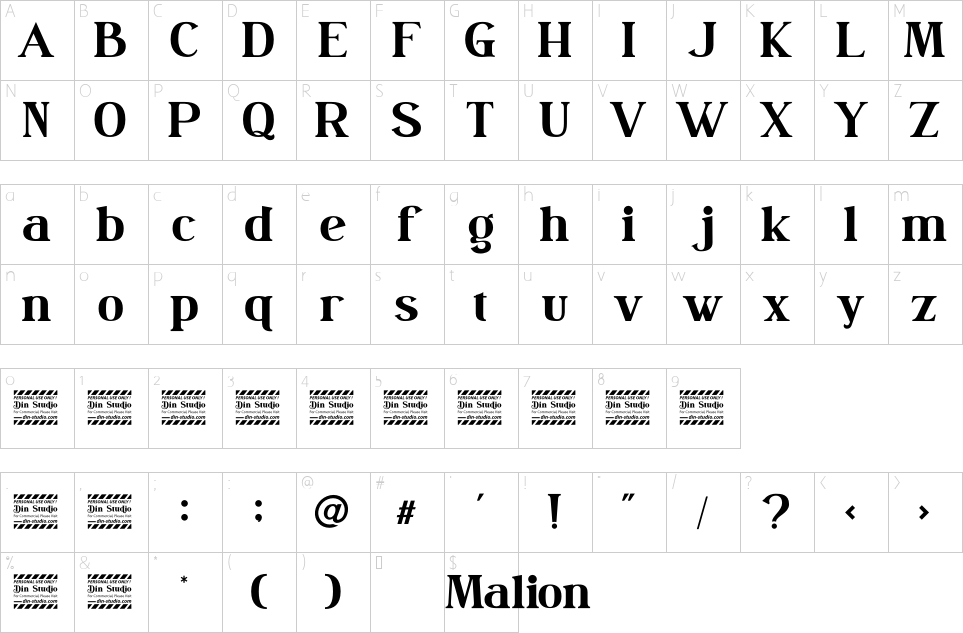
A Malion Font é uma fonte de graça ideal para designers e criadores de conteúdo que buscam uma opção moderna e elegante. Desenvolvida pela Din Studio, esta fonte oferece uma variedade de tamanhos e estilos, tornando-a perfeita para diversas aplicações de design, desde logotipos e gráficos até designs web e publicações digitais. Com seu design minimalista e arquitetado para um uso fluido, a Malion Font é uma escolha ideal para quem busca uma fonte clara e moderna para seus projetos. A fonte foi baixada cerca de 3,584 vezes, demonstrando sua popularidade entre designers e criadores de conteúdo. Se você está procurando por uma fonte de qualidade para seus projetos, a Malion Font é uma ótima opção para adicionar ao seu portfólio.